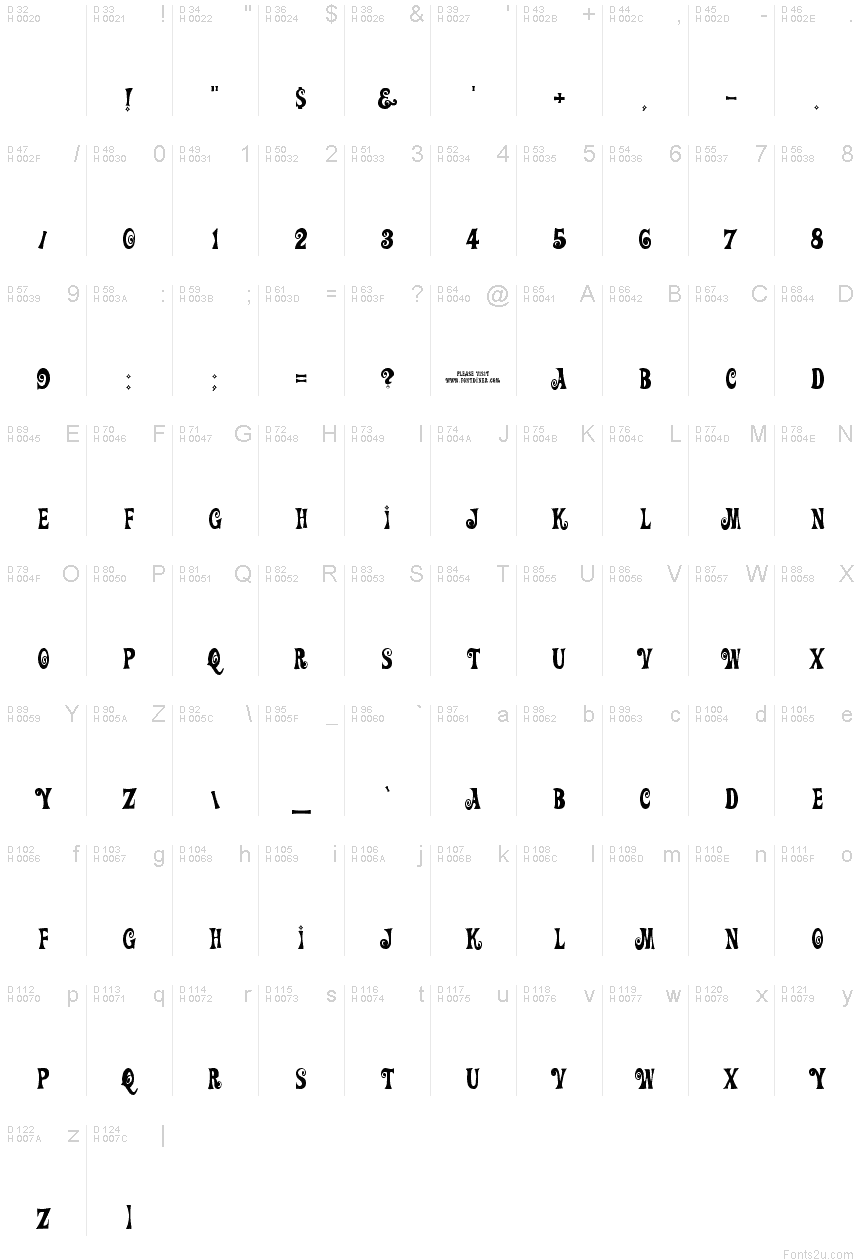
ActionIs autorstwa B.O.Nelson / Brain Eaters Font Co. to darmowy, zakręcony krój displayowy z dzikim, hipnotyzującym twistem. Grube, atramentowe pociągnięcia pęcznieją i przechodzą w spirale, kojarzące się z karnawałem i nawiedzonym domem, nadając każdemu słowu dynamiki i psotnego charakteru. Specyficzne, diamentowe wykończenia i zawijasy przyciągają wzrok, sprawiając, że nawet krótki nagłówek ożywa na stronie.
Ten darmowy font najlepiej sprawdza się na plakatach na Halloween, ulotkach w stylu cyrkowym, zaproszeniach, okładkach książek, tytułach gier i wyrazistych logotypach. Wygląda najlepiej w dużym rozmiarze, gdy jej loki i zawijasy mają przestrzeń; połącz ją z czystym, neutralnym krojem bezszeryfowym w tekście głównym, aby chaos był uroczy, a nie przytłaczający.